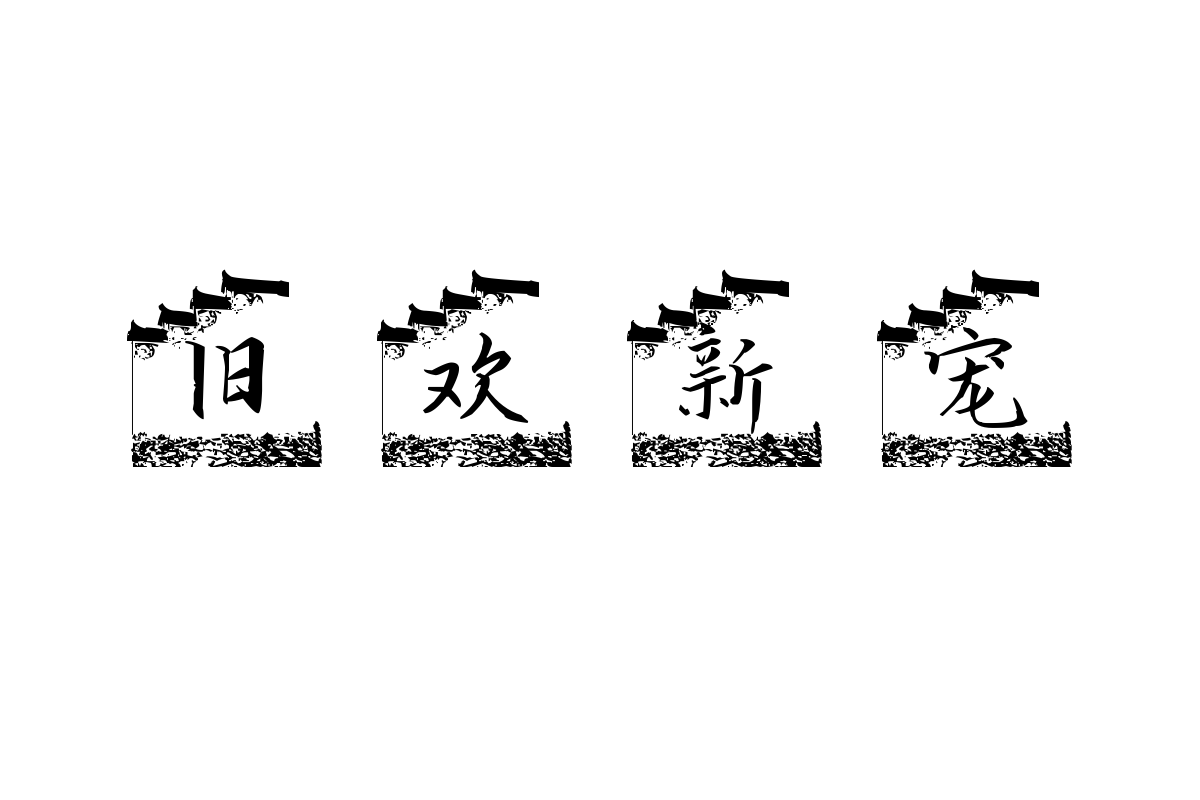
汉呈徽派字体是一种具有中国传统书法韵味的字体,它以楷书为基础,融入了徽州地区特有的书法风格和元素。这种字体的特点是笔画流畅、结构严谨、字形饱满,给人一种古朴典雅的感觉。
汉呈徽派字体的主要特点如下:
1. 笔画流畅:汉呈徽派字体的笔画流畅自然,没有过多的装饰性笔触,给人一种简洁明快的感觉。
2. 结构严谨:汉呈徽派字体的结构严谨,每个字的笔画都经过精心设计,使得整个字体看起来整齐划一。
3. 字形饱满:汉呈徽派字体的字形饱满圆润,线条粗细适中,给人一种稳重的感觉。
4. 融合徽州特色:汉呈徽派字体在保留传统楷书的基础上,融入了徽州地区特有的书法风格和元素,如徽派篆刻、徽派山水画等,使得字体既有传统韵味,又具有地方特色。
5. 适用场景广泛:汉呈徽派字体适用于各种场合,如书籍、杂志、广告、包装等,既能展现中国传统文化的魅力,又能适应现代设计的需求。
总之,汉呈徽派字体是一种具有中国传统书法韵味的现代字体,它既保留了传统楷书的基本特征,又融入了徽州地区特有的书法风格和元素,是一种非常具有特色的字体。